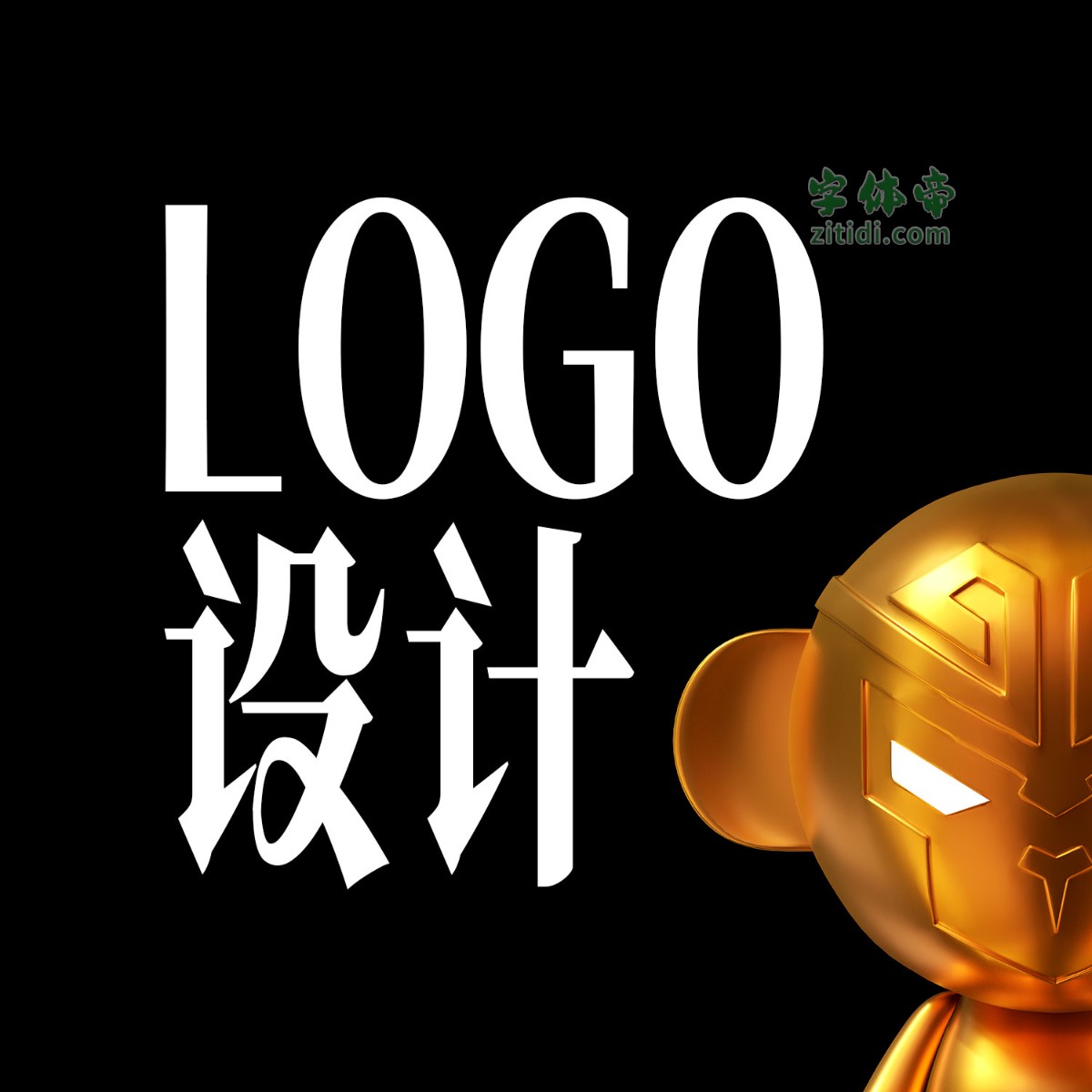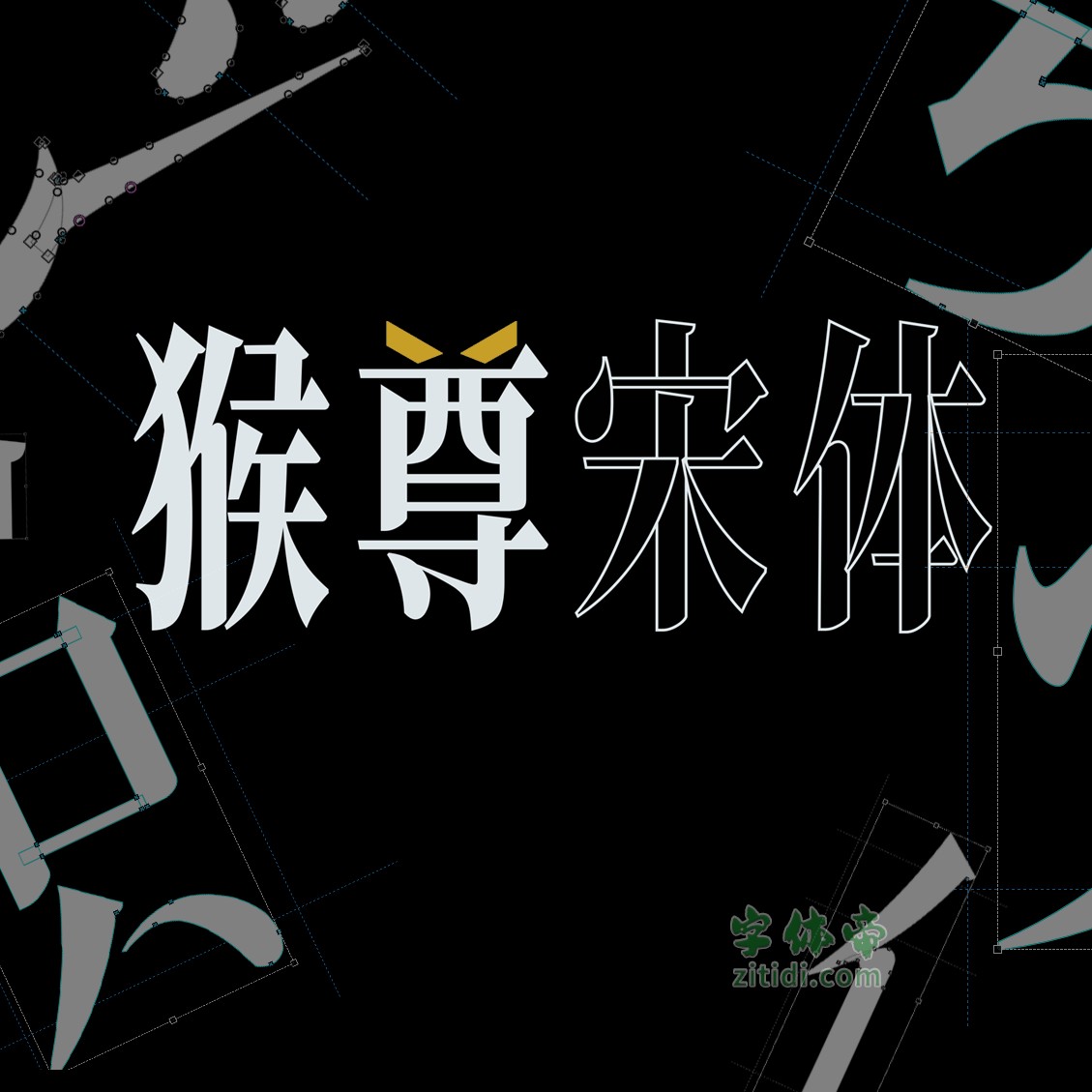
猴尊宋体是由抖音设计博主猴尊提供的一款免费商用字体,基于思源字体的比例更改为黄金比例值,部分字体笔画、字母、数字、符号等字体重构设计,为短视频的手机竖屏阅读时,一行文字可放下更多(更大)的字,用于大标题时,依具精致感。字体保留原笔画不合并(转曲线后可见,你可随意继续创新),个别笔画加入书法手写的笔画感觉,字体有种独特高雅的高级感!
“猴尊宋体”是一款书写很新颖的字体,字体大方,适合各种设计作品使用!欢迎下载!